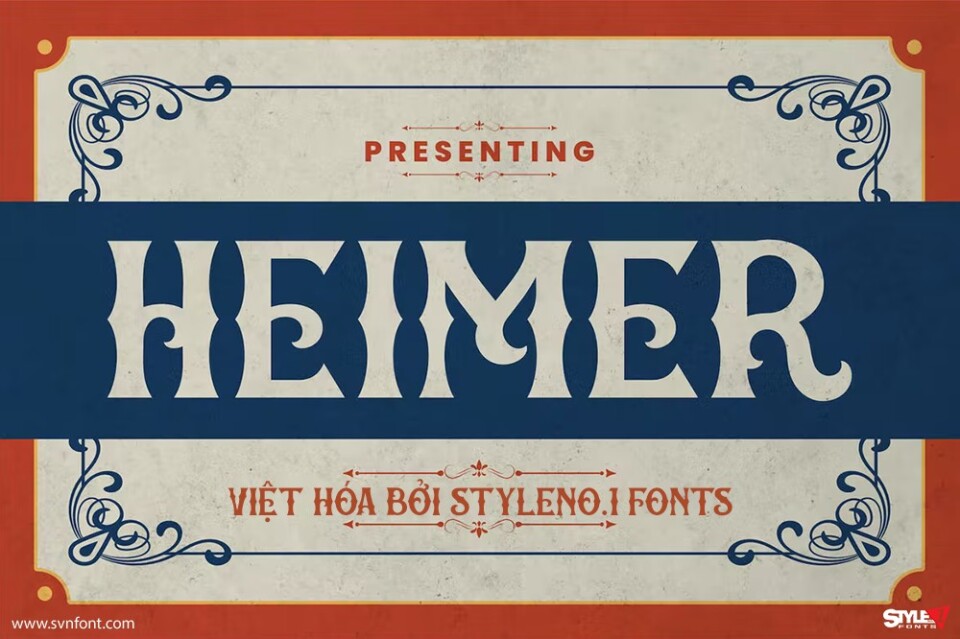
Font việt hóa SVN Heimer – Lựa chọn hoàn hảo cho thiết kế sáng tạo
Giới thiệu về Font việt hóa SVN Heimer trong thiết kế đồ họa
Trong thế giới sáng tạo, việc lựa chọn một Font Chữ phù hợp đóng vai trò quyết định đến sự thành công của một tác phẩm nghệ thuật. Font việt hóa SVN Heimer là một bộ phông chữ mang phong cách hiện đại, thanh lịch nhưng không kém phần mạnh mẽ. Đây là phiên bản được tối ưu hóa hoàn toàn cho ngôn ngữ tiếng Việt, giúp các bạn học sinh và nhà thiết kế dễ dàng áp dụng vào các bài thuyết trình hay dự án cá nhân mà không lo lỗi hiển thị dấu câu.
Đặc điểm nổi bật của bộ Font việt hóa SVN Heimer
Bộ phông chữ này sở hữu các đường nét tinh tế, độ tương phản vừa phải, tạo cảm giác dễ nhìn và chuyên nghiệp. Font việt hóa SVN Heimer không chỉ phù hợp cho các tiêu đề lớn mà còn hoạt động tốt trong các đoạn văn bản ngắn. Với sự đa dạng trong các định dạng từ mảnh đến đậm, người dùng có thể linh hoạt phối hợp để tạo nên sự phân cấp thông tin rõ ràng, giúp người xem dễ dàng tiếp nhận nội dung quan trọng nhất.
Ứng dụng thực tế và cách sử dụng hiệu quả
Bạn có thể sử dụng bộ phông này cho nhiều mục đích khác nhau như thiết kế poster trường học, bìa sách hoặc các ấn phẩm truyền thông mạng xã hội. Khi sử dụng Font việt hóa SVN Heimer, hãy lưu ý kết hợp với các màu sắc trung tính để làm nổi bật sự sang trọng của bộ chữ. Việc tận dụng các khoảng trắng xung quanh chữ cũng giúp thiết kế trở nên thoáng đãng và hiện đại hơn, phù hợp với xu hướng thẩm mỹ tối giản hiện nay.
Kết luận về giá trị của phông chữ này
Tóm lại, việc sở hữu một bộ phông chất lượng như phông chữ này sẽ giúp nâng tầm giá trị cho mọi sản phẩm thiết kế của bạn. Nếu bạn đang tìm kiếm một công cụ hỗ trợ đắc lực cho việc trình bày nội dung tiếng Việt một cách chỉn chu, đừng bỏ qua bộ Font Miễn Phí, Font Việt Hóa, Font việt hóa SVN Heimer để trải nghiệm sự khác biệt trong từng nét chữ và tạo nên những tác phẩm ấn tượng nhất.